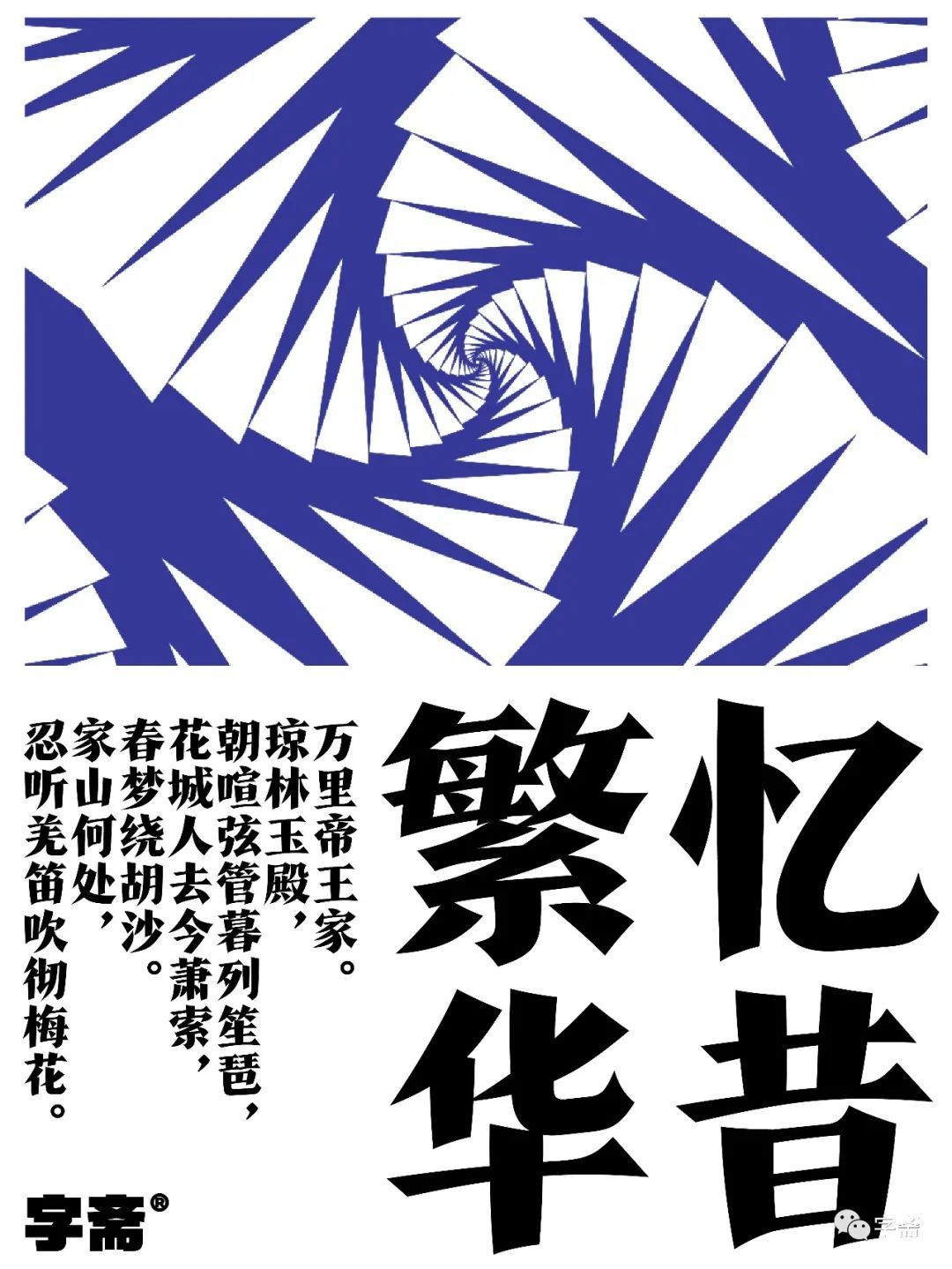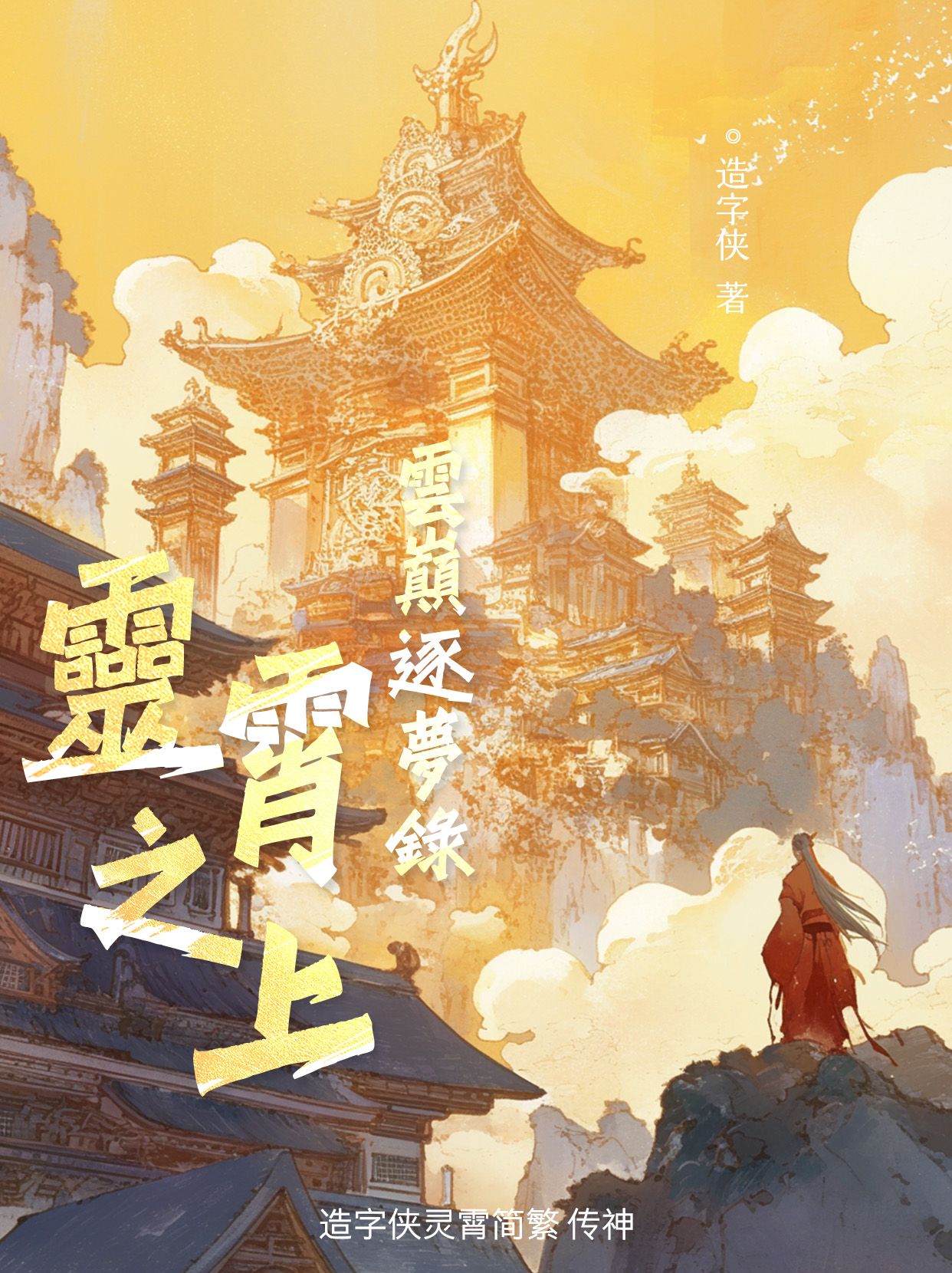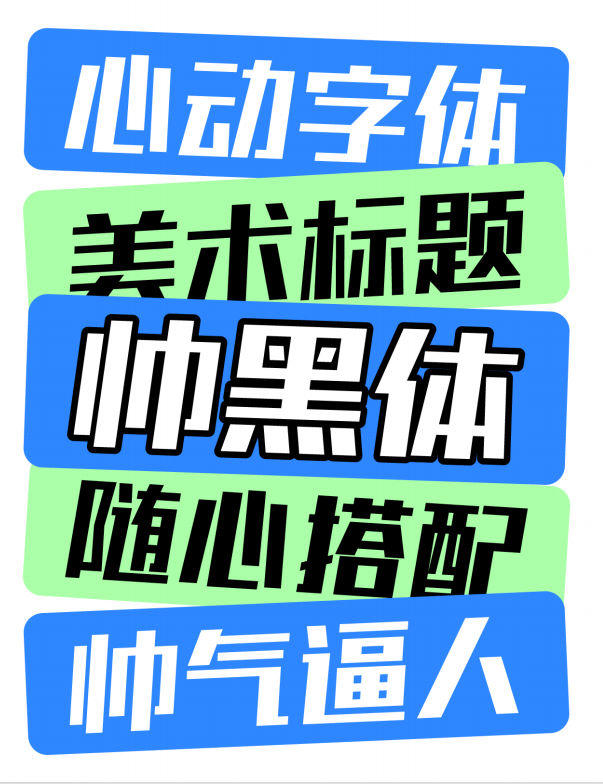
中秋佳节,用最美字体装点月饼礼盒 —— 四款精选字体推荐
中秋节即将来临,无论是传统还是创新口味的月饼,精美的包装设计总是不可或缺的一部分。字体作为视觉传达的重要元素之一,在设计中起着至关重要的作用。今天,我们特别推荐四款适合用于月饼包装设计的字库字体,帮助您打造出独具特色的月饼礼盒,吸引更多消费者的目光。
1.造字侠郝刚快乐简 微黑
这款字体简洁而不失优雅,字形线条流畅,整体给人以舒适愉悦的感觉。造字侠郝刚快乐简 微黑非常适合用于传达中秋节团圆美满的主题,能够营造出温馨、和谐的节日氛围。无论是作为主标题还是点缀性文字,都能够很好地与月饼包装的整体风格相融合,传递出品牌的文化内涵。
2. 高手字斋东京体
字体的设计带有浓郁的现代都市气息,给人一种清新脱俗的感觉。它的笔画粗细变化自然,结构紧凑而富有弹性,适用于那些追求时尚简约风格的月饼包装设计。选择这款字体,可以让您的产品在众多传统设计中脱颖而出,吸引更多年轻消费者的目光。
3. 造字侠灵霄简繁 传神
这款字体融合了传统书法之美与现代设计感。无论是简体还是繁体,都能展现出汉字的独特魅力。将其应用于月饼包装设计中,不仅能体现中华文化的深厚底蕴,还能增强产品的文化认同感,适合那些注重文化底蕴的品牌使用。
4.高手庆科帅黑体 大黑
作为一款极具个性的黑体字,它不仅具备了黑体字清晰易读的优点,同时还加入了更多的设计感,使得每个字都充满了力量与动感。这样的字体非常适合用于强调品牌的独特性和高端品质,特别是在需要突出品牌LOGO或者重要信息时,能够有效吸引消费者的注意力。
总之,不同的字体能够赋予月饼包装设计以不同的风格和情感表达。在选择时,可以根据品牌定位、目标消费群体以及具体的设计需求来决定最适合的那款字体。希望以上的推荐能给您的创作带来灵感,让今年的中秋佳节更加精彩纷呈!